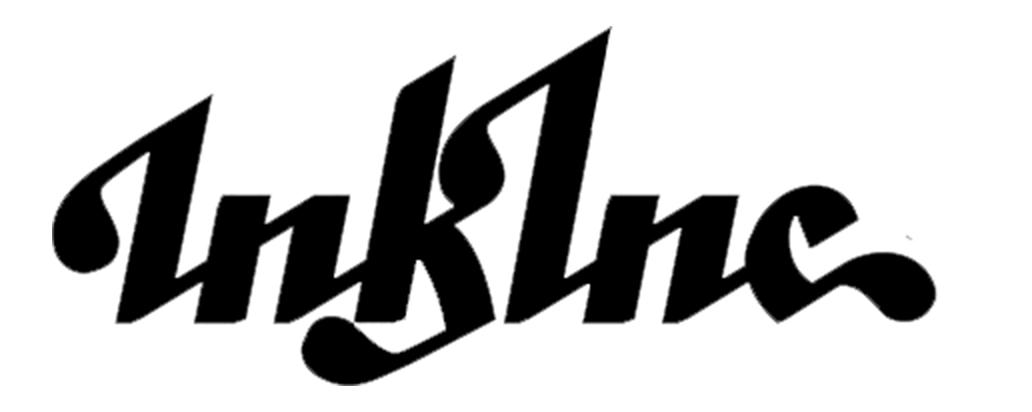
Schrift einer fiktiven Marke aus GTA
ich suche diese Schrift hier aus dem Spiel GTA. Sie gehört zu einem Tattooladen und ist somit vom Entwickler frei erfunden. Achtung der "Tropfen" am Ende vom 'c' ist ein Punkt.
wenn die Schrift eine Erfindung für ein Spiel war, wird es die nicht wirklich digital geben, denk ich... also suchst Du eine Ähnliche?
Mit dem Hinweis, kann ich es auch lesen – Tinten Gesellschaft :oops:
Das wird wahrscheinlich gezeichnet, oder zumindest stark verändert wurden  sein. Ansonsten mal bei dafont.com oder so durchgucken, ob sich da was findet :-?